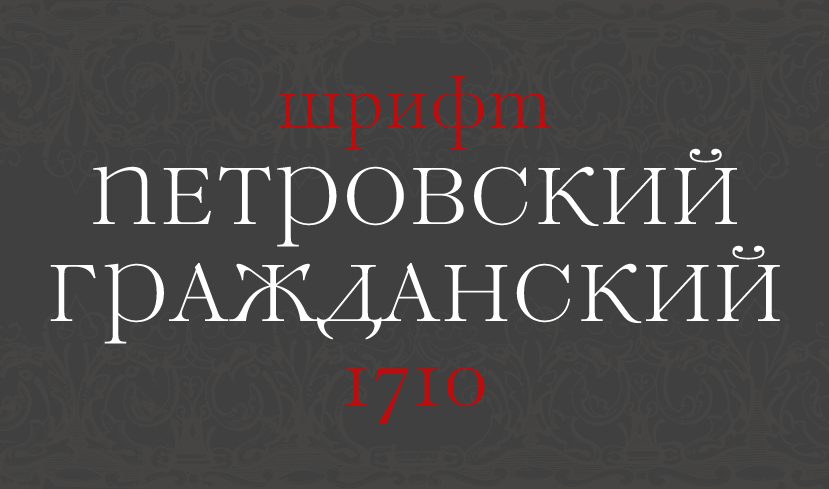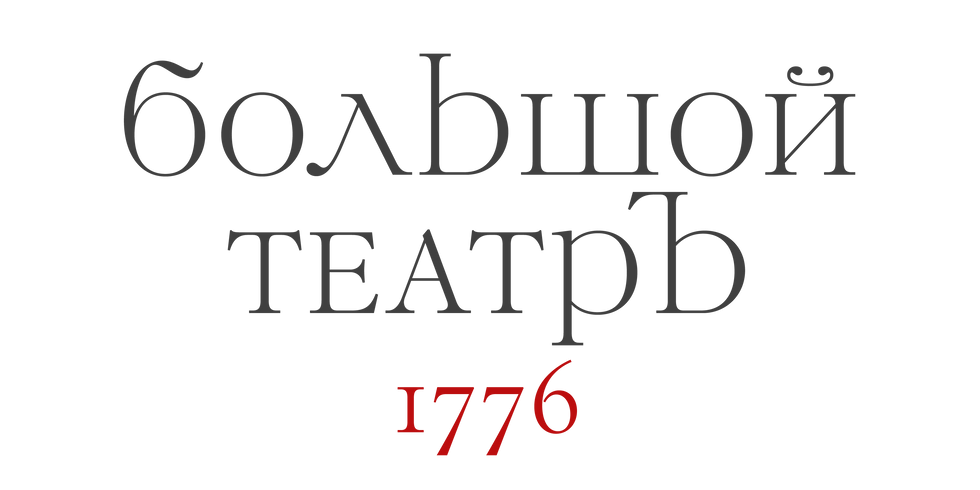
Обновление шрифта Петровский гражданский/DXGrazhdanskiy1710.
Обновлен шрифт DXGrazhdanskiy1710 - цифровой версии металлического шрифта "Петровский гражданский" Словолитни О.Лемана. В новой версии переработан рисунок и скорректированы пропорции знаков, спроектирован дополнительный набор цифр, расширен набор лигатур и альтернативных знаков.